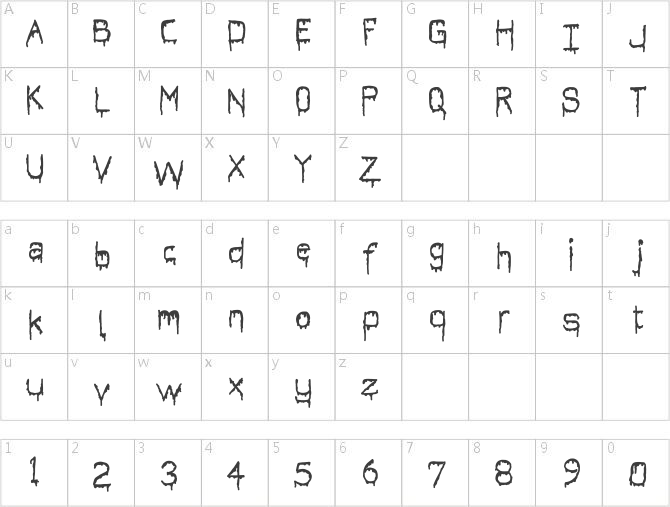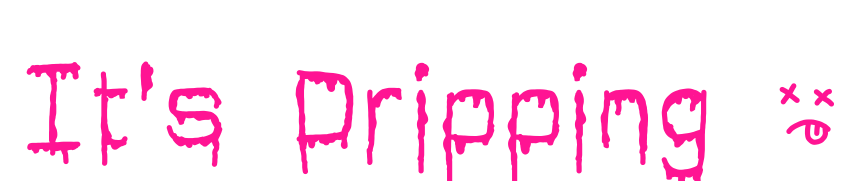
It's Dripping ~ 詳情頁(yè)
It's Dripping ~字體字庫(kù)是一款讓人賞心悅目、百看不厭的英文字體,適合各類(lèi)廣告和產(chǎn)品包裝設(shè)計(jì)應(yīng)用,字體大小0.1MB,格式為ttf字體,上傳用戶(hù)是漫步云端,作者/版權(quán)方為未知